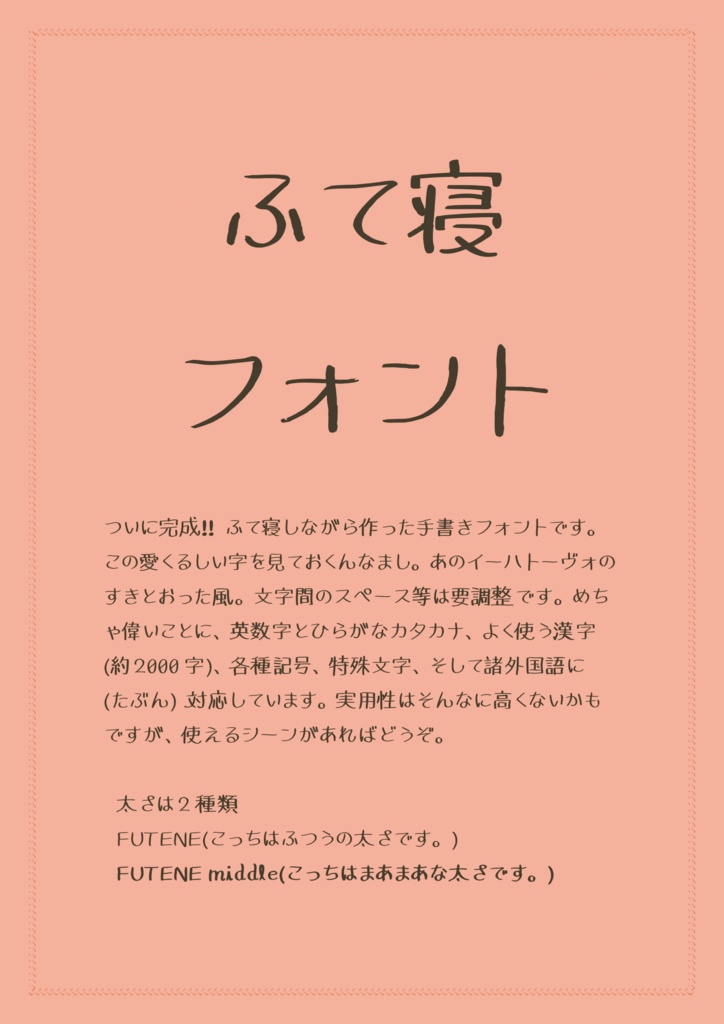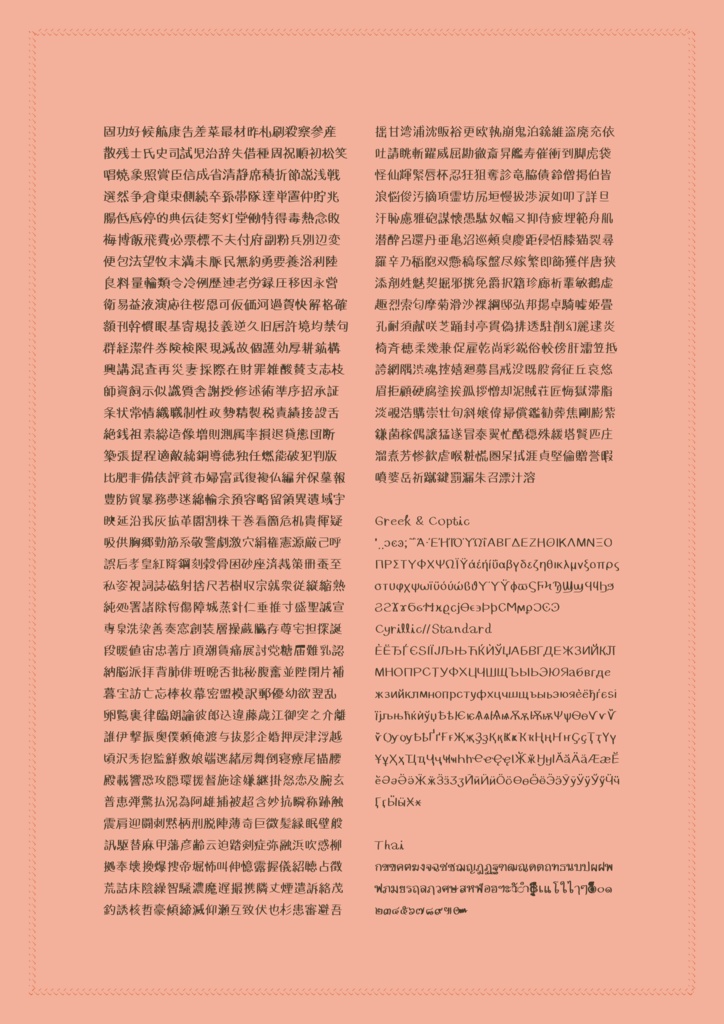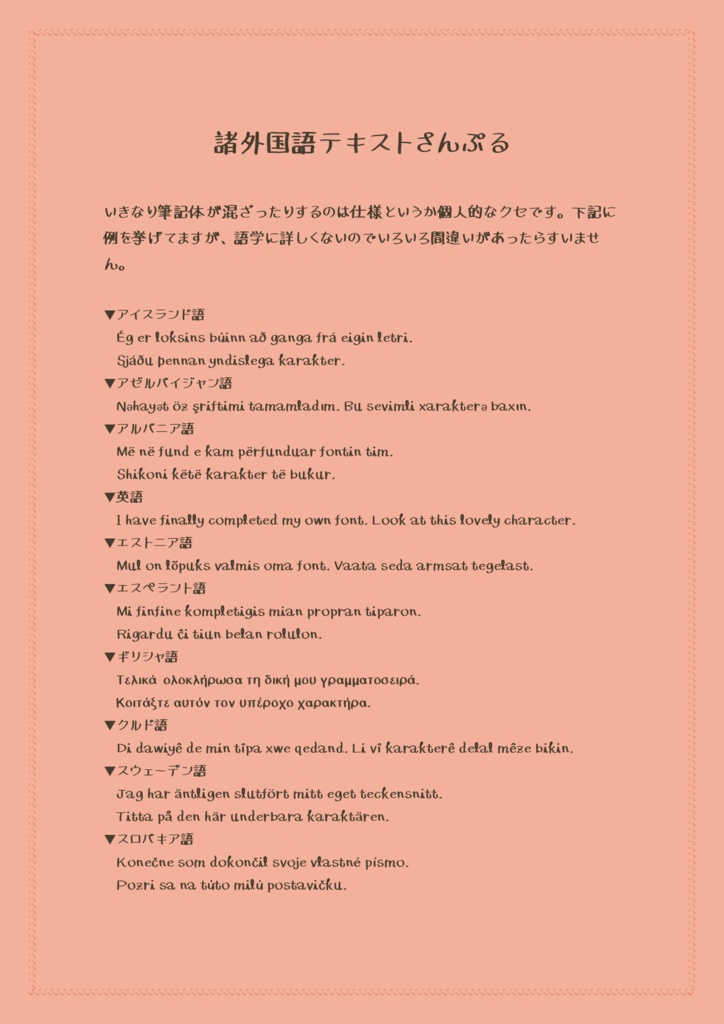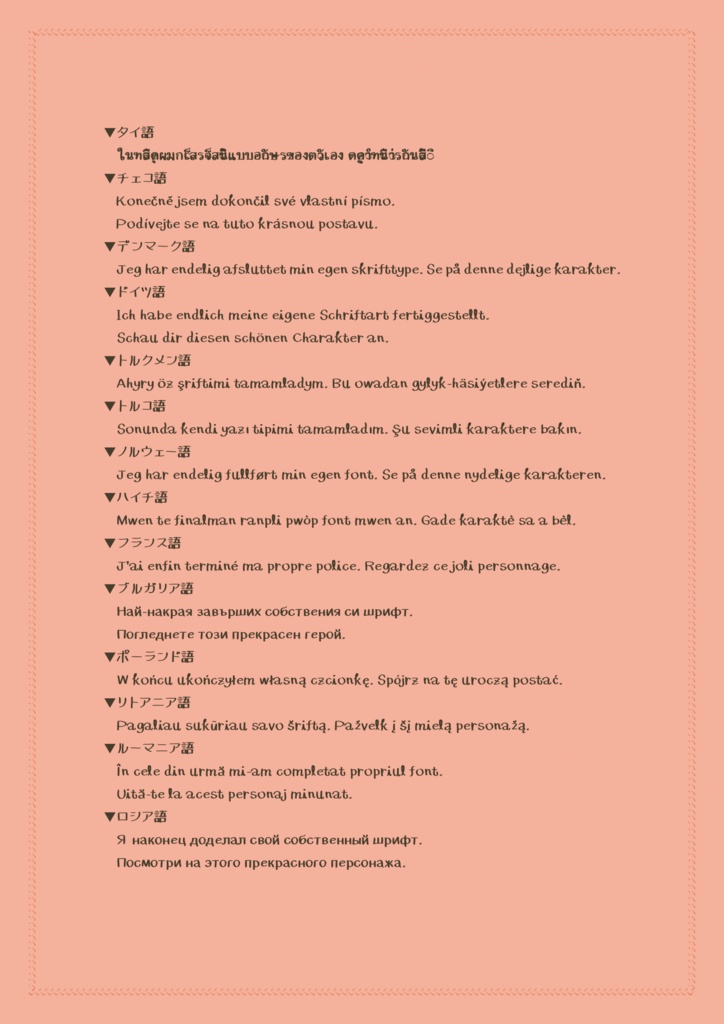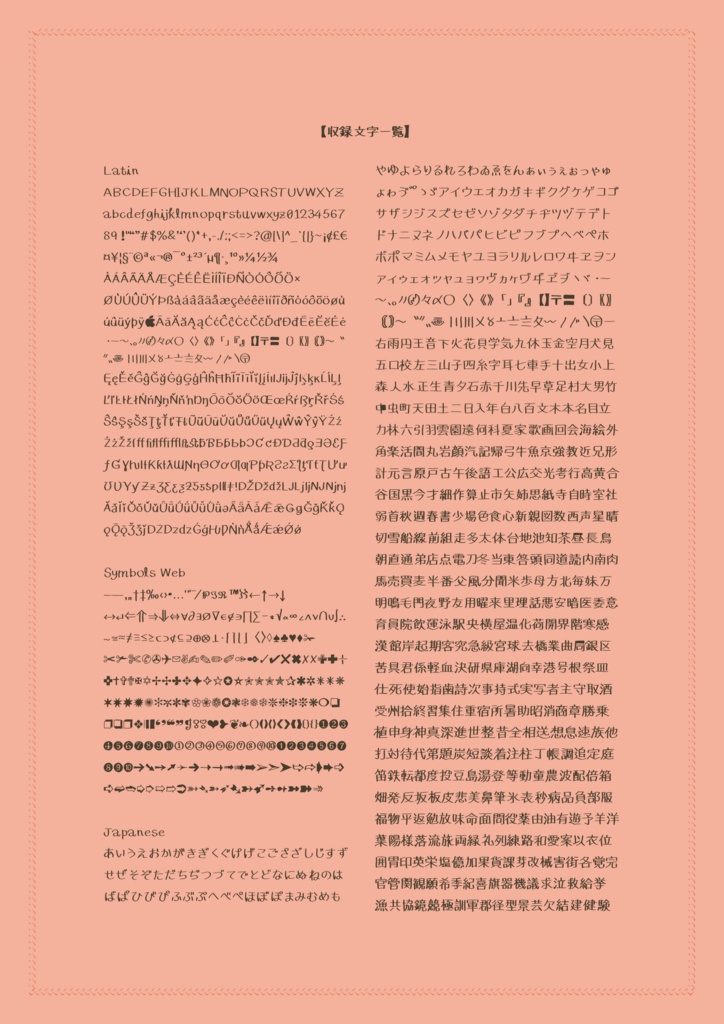
ふて寝フォント(フリーフォント/商用・同人誌利用可)
(告知)※データに色々とミスがあったため、現在修正版を作成中です。修正が済み次第SNS上で告知し、このページに追加します。すでにダウンロードいただいた方は申し訳ありません。 自分で使用するために作った手書きフォントです。英数字とひらがなカタカナ、よく使う漢字(約2000字)、 各種記号、特殊文字、そして諸外国語に (ちょっと) 対応しています。詳しくはサンプルをご覧ください。試作品なので完成度はへなちょこですが、使えるシーンがあればご自由にご利用ください。 ●True typeフォントです。 ●太さはFUTENE(ふつうの太さ)とFUTENE middle(まあまあな太さ)の2種類です。 ●記号など、文字間のスペース等は要調整です。 ●商用・同人誌利用可能です。クレジット記載やご使用報告は不要ですが、ご連絡いただけたら嬉しいです。